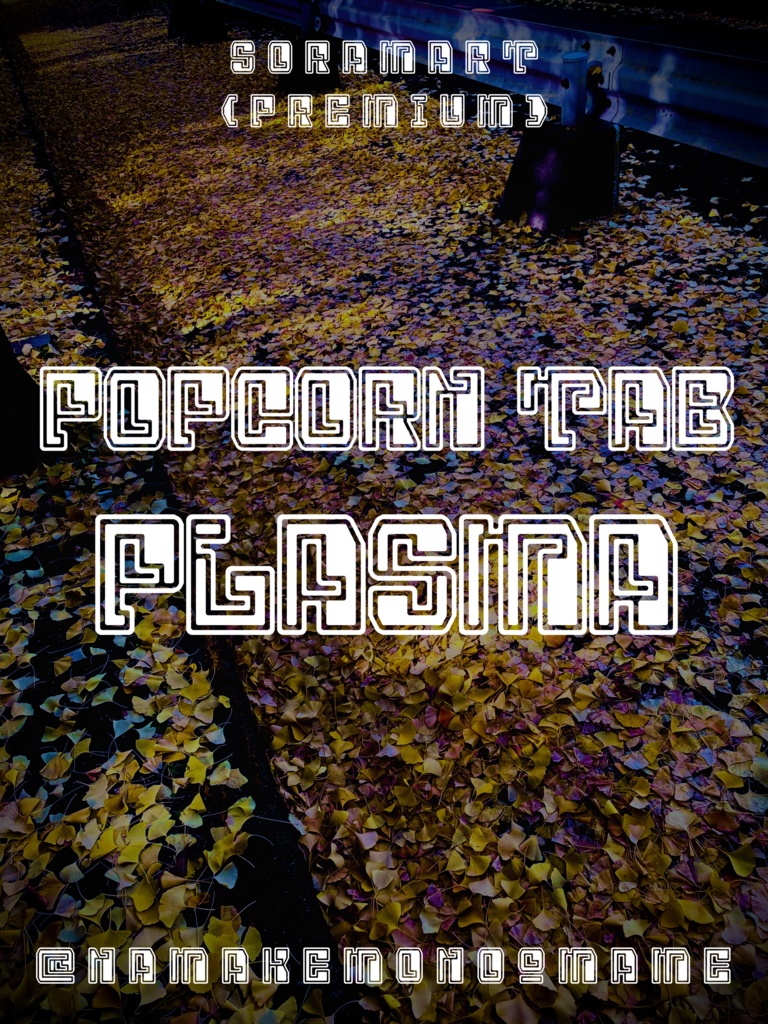
そらマートフォントデータ”Popcorn Tab Plasma”Digital2,500 JPYAdd to CartBuy a GiftAbout Gift切り欠き装飾を加えたポップ調太字フォントに、サイバー調の白抜き装飾を加えた "Popcorn Tab Plasma" です。 「TrueTypeフォントファイル」という形式です。 ダウンロードした後、Zipファイル内のデータをインストールしてお使いください。 このフォントは商用利用可となっております。 お客様の制作・創作活動のお役に立てれば幸いです。 ※使用上の注意事項などは、添付のReadmeをお読みください。 ※このフォントは、有料販売限定商品です。そらマートVisit FANBOX!Fontsフォントデータ”Tonik Crate”そらマート0 JPYFontsフォントデータ”Vapor Sprout Edge”そらマート2,500 JPYFontsフォントデータ”Vapor Sprout Wide”そらマート2,500 JPYFontsフォントデータ”Vapor Sprout”そらマート2,500 JPYFontsフォントデータ”Star Shoot Ray”そらマート2,500 JPYFontsフォントデータ”Star Shoot Black Wide”そらマート2,500 JPYFontsフォントデータ”Star Shoot Black”そらマート2,500 JPYFontsフォントデータ”Mars Invader Balloon”そらマート2,500 JPYFontsフォントデータ”Mars Invader Wide”そらマート2,500 JPYFontsフォントデータ”Mars Invader”そらマート2,500 JPYFontsフォントデータ”Rock Cut Serif”そらマート2,500 JPYFontsフォントデータ”Rock Cut Drop Wide”そらマート2,500 JPYFontsフォントデータ”Rock Cut Drop”そらマート2,500 JPYFontsフォントデータ”Longtail Sans Serif Slashed”そらマート2,500 JPYFontsフォントデータ”Longtail Sans Serif Bold”そらマート2,500 JPYFontsフォントデータ”Longtail Sans Serif”そらマート2,500 JPYFontsフォントデータ”Pretty Commando”そらマート2,500 JPYFontsフォントデータ”Abyss Dive Punk Retro”そらマート2,500 JPYFontsフォントデータ”Abyss Dive Punk Wide”そらマート2,500 JPYFontsフォントデータ”Abyss Dive Punk”そらマート2,500 JPYSee More